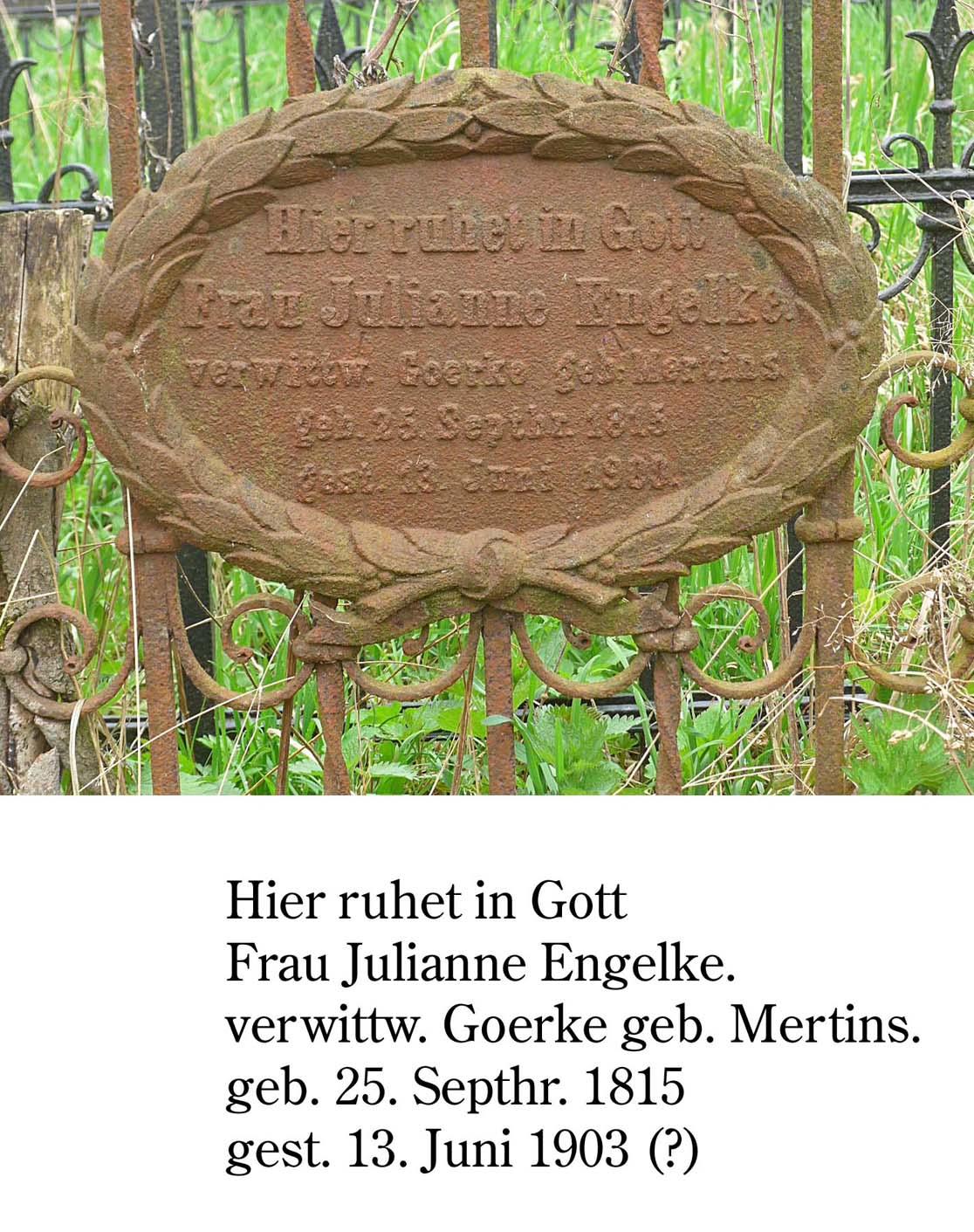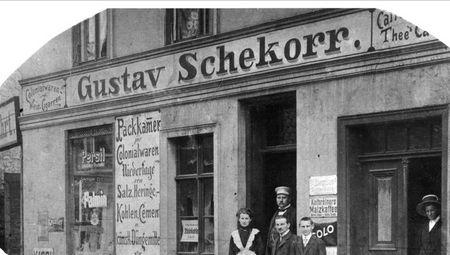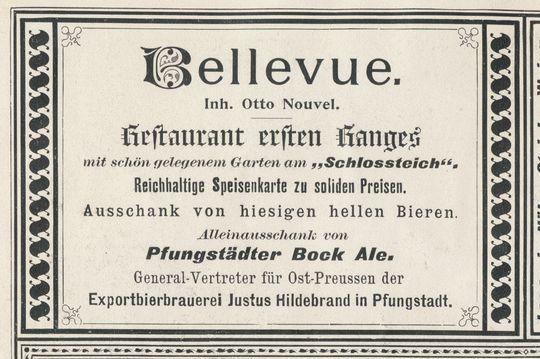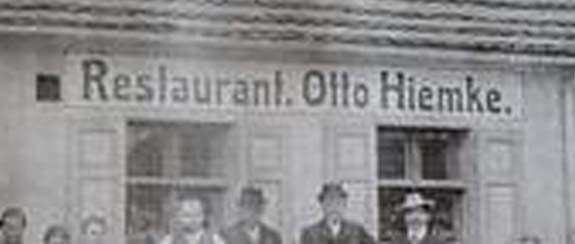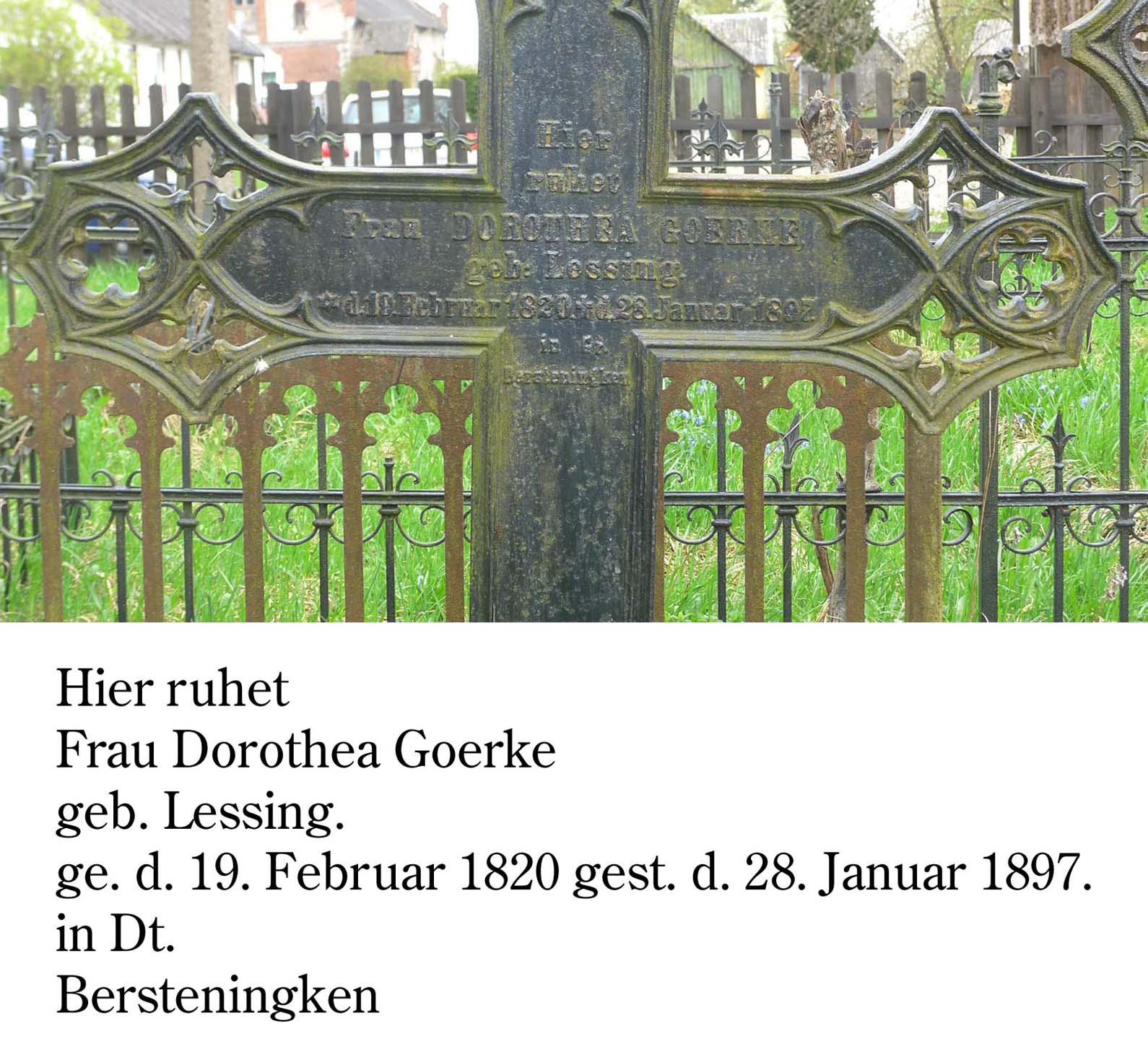
Punkt hinter einzelnen Worten bei alten Grabkreuzen
bei alten gusseisernen Grabkreuzen ist mir aufgefallen, dass manchmal hinter Namen oder Datum ein Punkt steht. Ebenso bei gemalten Bezeichnungen an Häusern aus der Gründerzeit:  Gartenrestaurant. Wilhelm Müller. Was war der Grund für diese Punktsetzung? War es eine grammatikalische Modeerscheinung?
Ursprünglich setzte man auch nach freistehenden Zeilen (in Inschriften, Anzeigen, Überschriften, Bildunterschriften, Anreden usw.) und nicht nur nach vollständigen Sätzen häufig einen Punkt. Selbst der Duden machte das bis zur 9. Auflage (1915) so. Vor der Rechtschreibreform war der Punkt (bzw. seine Weglassung) nach freistehenden Zeilen nicht geregelt, sondern folgte nur dem verbreiteten Usus.